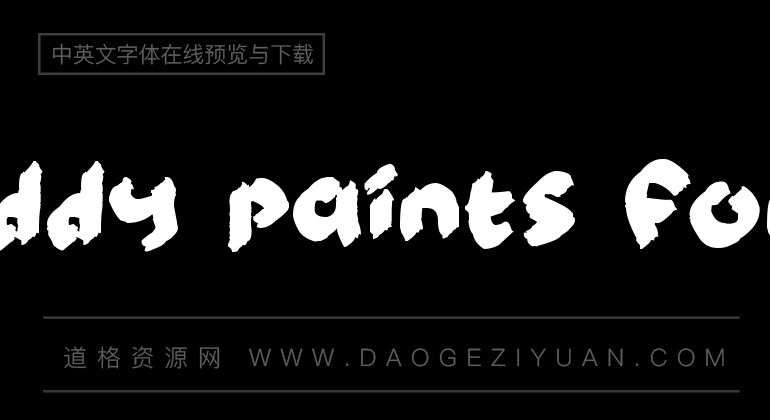
Kiddy Paints Font 字体是一种手写风格的字体,具有卡通和儿童风格的特点。这种字体被设计成类似于孩子们在画板上创造的涂鸦和画作,充满着乐趣和创意。Kiddy Paints Font 字体有两种版本,一种是实心字体,另一种是轮廓字体,可以根据需要进行选择使用。 这种字体非常适合用于儿童书籍、教育材料、儿童游戏、广告宣传、海报和卡片等设计项目中。它可以为设计带来趣味性和亲和力,并且可以吸引孩子们的注意力,增加他们对内容的兴趣和参与度。内容介绍
Kiddy Paints Font是一款非常不错的手写艺术字体,具有很好的视觉感,适合于文化类的宣传设计、商业类品牌的广告和产品包装设计以及个性化文字排版等较多场景。